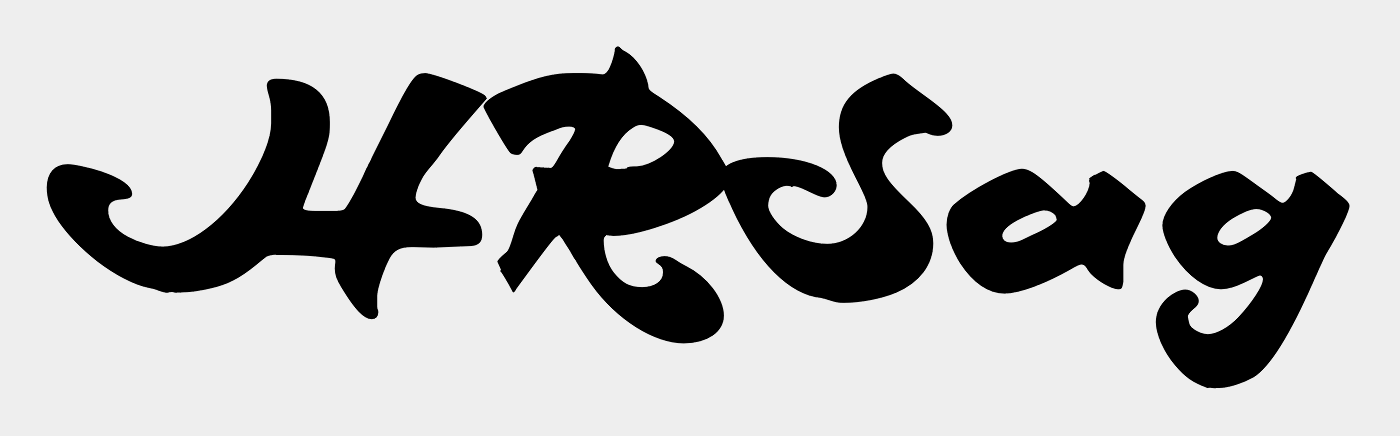
Maxim was originally designed by Peter Schneidler in 1956 for the Bauer foundry.
Ralph M. Unger redrew and digitized this font in 2003. His work is based on artwork taken from old font catalogs.